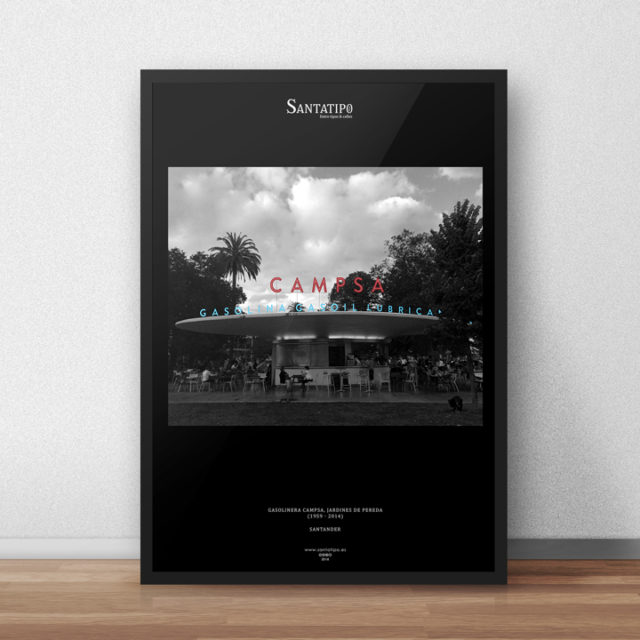
[Poster] Rótulo de la vieja gasolinera de los Jardines de Pereda
Uno de los elementos que ha sobrevivido a la reestructuración de los nuevos Jardines de Pereda, es la Gasolinera que estuvo activa entre 1959 y 2014. Ya recuperamos su rótulo y conocimos su historia aquí. Ahora si el rótulo original de mediados del Siglo XX con su neón, se hubiese mantenido, probablemente disfrutaríamos de algo tan icónico como esto